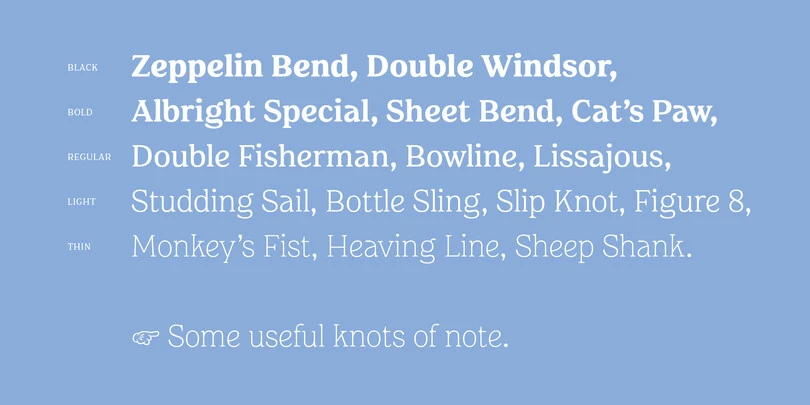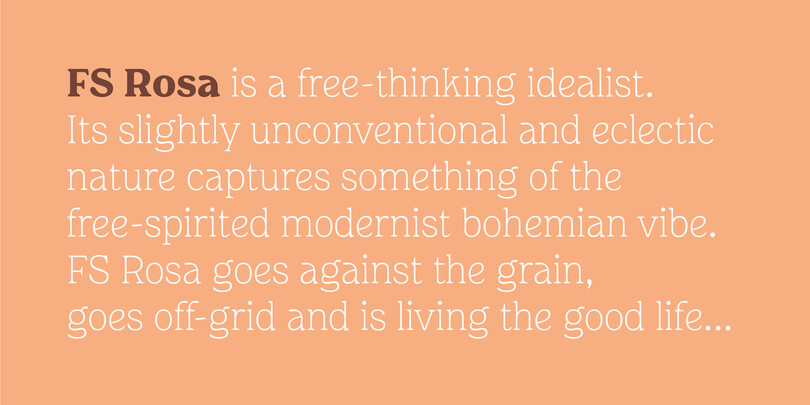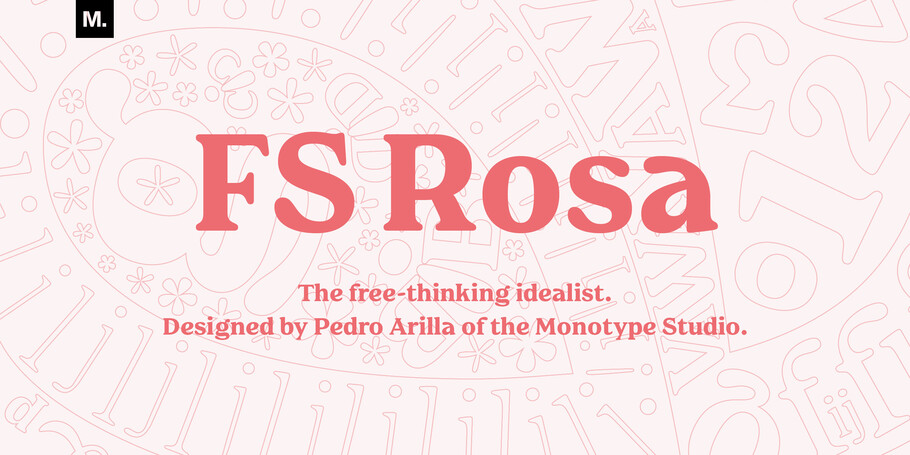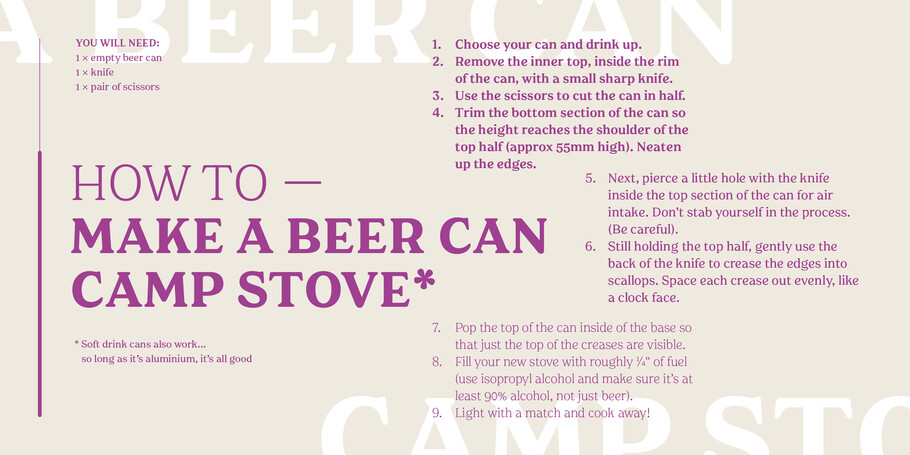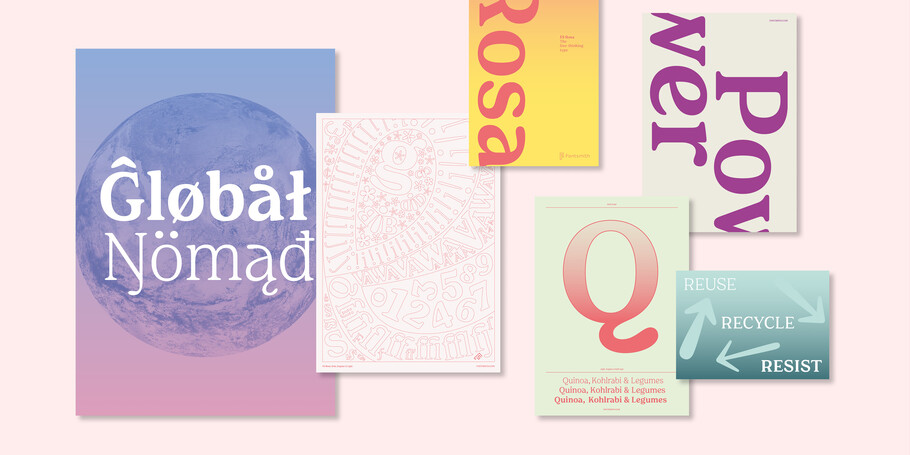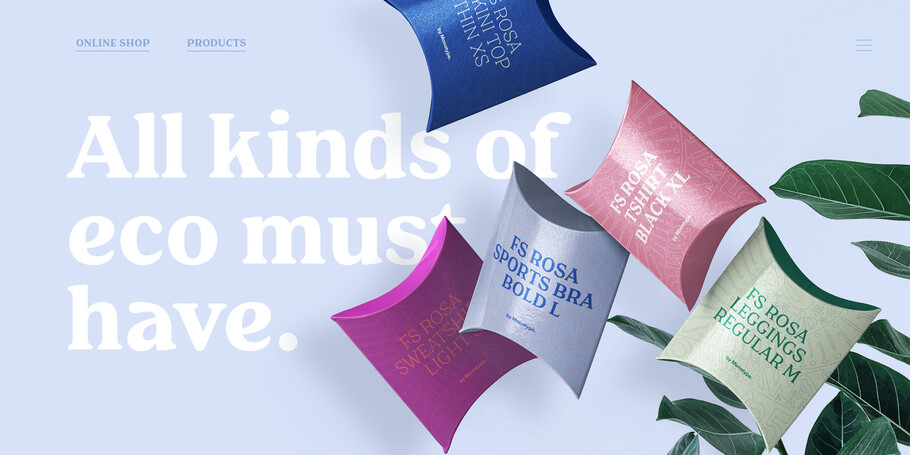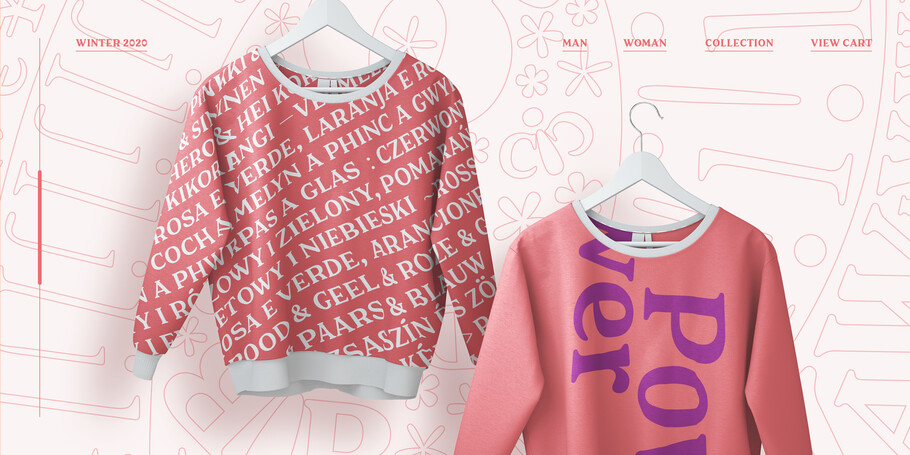
FS Rosa : chaleureux, décalé, avec un brin de nostalgie.
“ Je voulais que FS Rosa soit éclectique et brut dans ses formes de lettres, tout en restant accueillant et accessible. ”
Pedro Arilla.
Les caractères à empattement (serif) sont parfois considérés comme étant de nature sérieuse et ouvertement intellectuelle, une forme plus austère de leur homologue décontractée : le sans serif. Mais FS Rosa s’écarte de ces conventions en combinant l’élégance classique d’un serif par la chaleur et la légèreté créées par ses formes et courbes rondes.
Je voulais créer une nouvelle police de caractères qui s’éloigne de l’uniformité des sans serif géométriques lisses et élégants que l’on voit partout aujourd’hui, et exploiter quelque chose de plus humain et de plus accessible. Je suis lassé par la conquête permanente de la perfection numérique, je voulais créer quelque chose de plus varié et de plus coloré.
Je me suis donc tourné vers quelque chose de plus nostalgique et j’ai commencé à  m’intéresser aux polices serif qui étaient en plein essor dans les années 20 - de beaux classiques comme Cooper, Souvenir et Windsor qui ont ensuite connu une réapparition dans les années 70, figurant sur les couvertures de magazines de science-fiction, les pochettes de vinyles et les génériques de films. Je voulais leur donner une touche de modernité et créer un hommage typographique de cette époque.
En travaillant numériquement mais à main levée, j’ai commencé par développer un grammage régulier pour FS Rosa, puis je suis passé aux graisses plus lourdes pour finir par les plus légères. J’ai d’abord donné un contraste plus élevé au gras, le rendant prédominant comme police d’affichage, mais j’ai abandonné cette idée car je voulais faire briller les cinq graisses. Le noir est souvent le choix le plus populaire pour ce style de police, mais je voulais préserver l’identité du FS Rosa dans les cinq graisses sans lui faire perdre sa valeur.
J’ai donc conçu les graisses les plus lourdes pour qu’elles soient parfaites pour des messages forts et des titres accrocheurs, une graisse ‘regular’ qui est fonctionnelle et robuste pour des textes plus longs, et des graisses ‘light’ qui sont plus élégantes et contemporaines. C’est une famille de caractères avec trois voix bien distinctes.
Je voulais que FS Rosa soit éclectique et brut dans ses formes, tout en restant amical et accessible. Comme beaucoup de ses homologues des années 1920, ses caractères sont chaleureux et arrondis, avec des terminaux souples, une grande hauteur et de larges ouvertures. Ces traits doux sont découpés par des ascendants et des descendants courts avec des empattements inclinés, des barres transversales inhabituellement basses sur les majuscules, et de nombreuses surprises peuvent être trouvées dans les caractères ; la queue sur le «Q» est particulière, le «e» semble sourire, le «f» a quasiment une coiffure rock’n’roll inspirée des années 1950.
À travers ces excentricités, FS Rosa est magnifiquement rustique. En regardant les premiers films et dessins animés, de vieux magazines et couverture de vinyles, je me suis inspiré des nuances et des jolis défauts des caractères créés avant l’ère numérique. Le Letraset et autres techniques de transfert à sec des années 1970, qui étaient si expressifs m’ont aussi beaucoup aidé.
Le résultat est une version contemporaine de ces techniques - une police de caractères diversifiée, non conventionnelle et individuelle, mais aussi robuste et épurée quand il le faut. Ce n’est pas une police de caractère agressive et à la mode, mais une revendication silencieuse, une force progressive vers le changement. Counter Studio a conçu pour FS Rosa une gamme d’images typographiques qui reflètent sa nature ouverte, composée de pages de recettes et d’instructions sur la façon de fabriquer sa propre canette de bière, ce qui illustre parfaitement la nature proactive, bricoleuse et populaire de cette police de caractères. Son nom aussi est inspiré par un sentiment d’optimisme - Rosa est un clin d’œil aux verres «teintés de rose», ainsi qu’à mes propres racines espagnoles.
C’est cette chaleureuse originalité qui fait que FS Rosa est parfait pour les marques, les médias, les campagnes, les publications imprimées, les sites web et pour toutes entreprises souhaitant inciter à un changement positif. Loin de l’austérité des serifs et de l’aspect trop poli des sans serifs, FS Rosa célèbre la beauté du naturel.